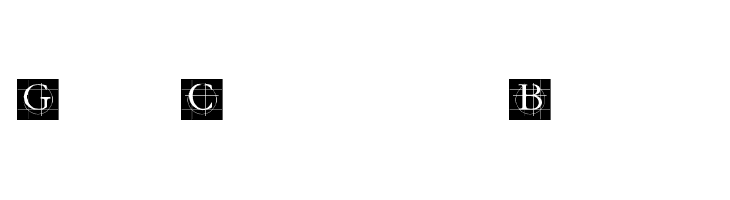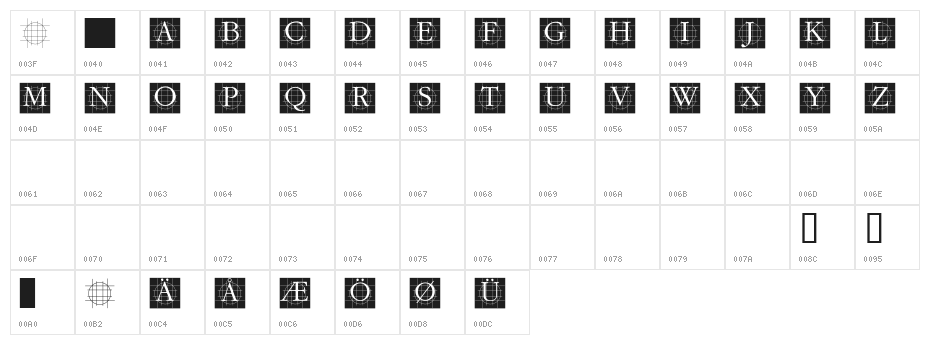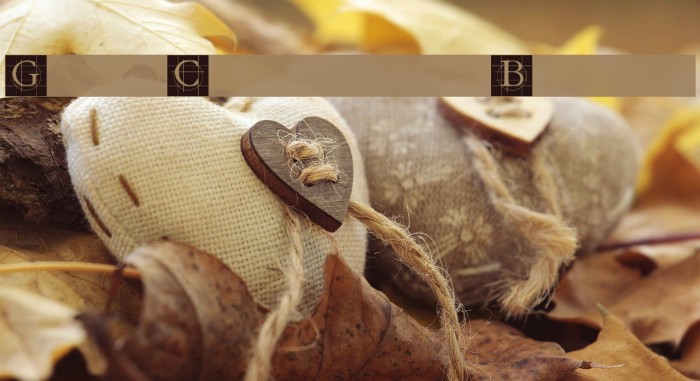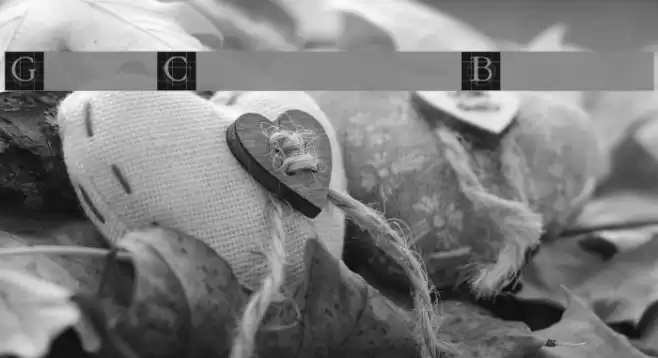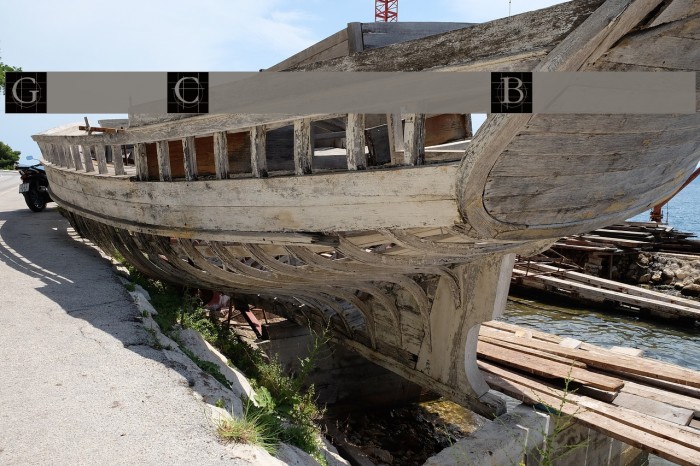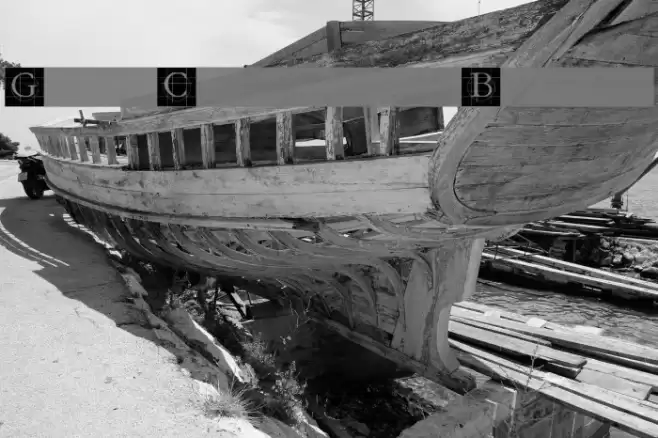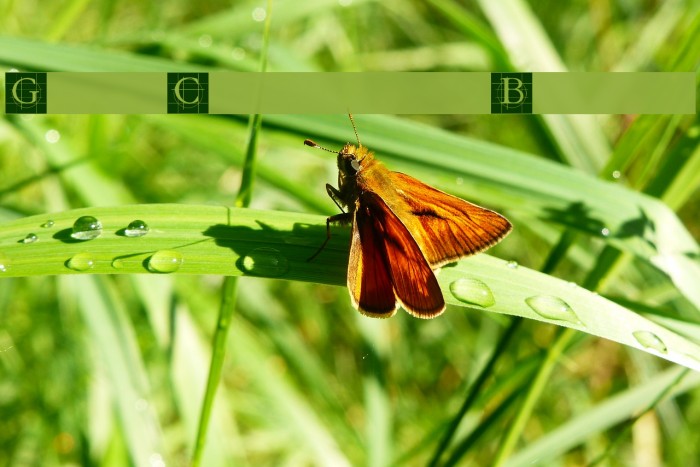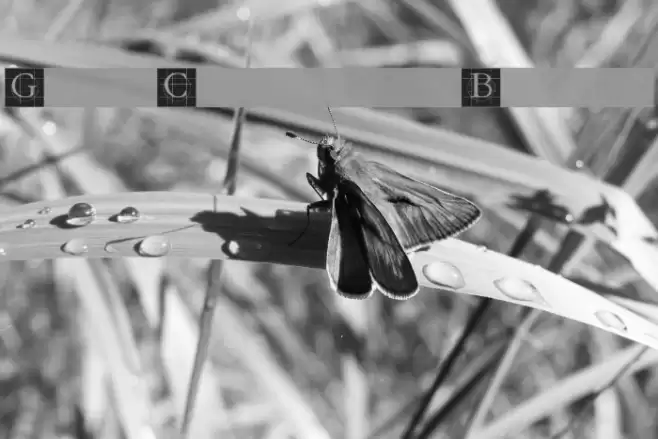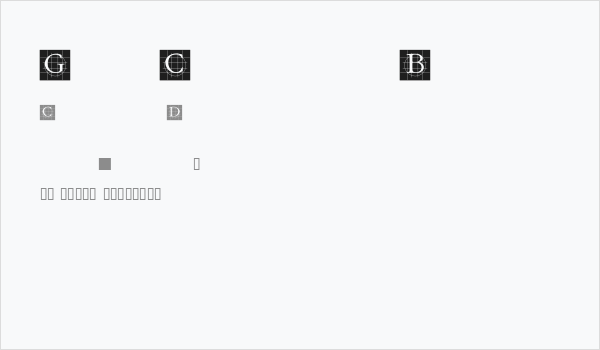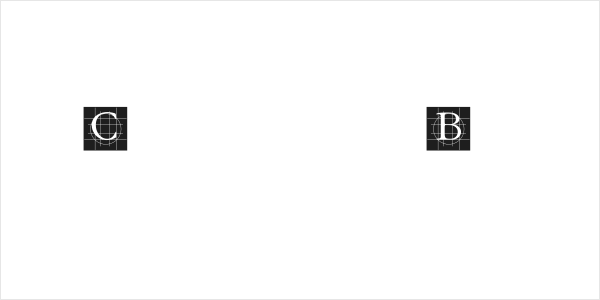
GrafCirculumBricks Font
| Anwendungsfall | Logos, Headlines |
| Vorgeschlagene Projekte | Ideal for architectural branding, technical illustrations, or any project requiring a modern and structured look. |